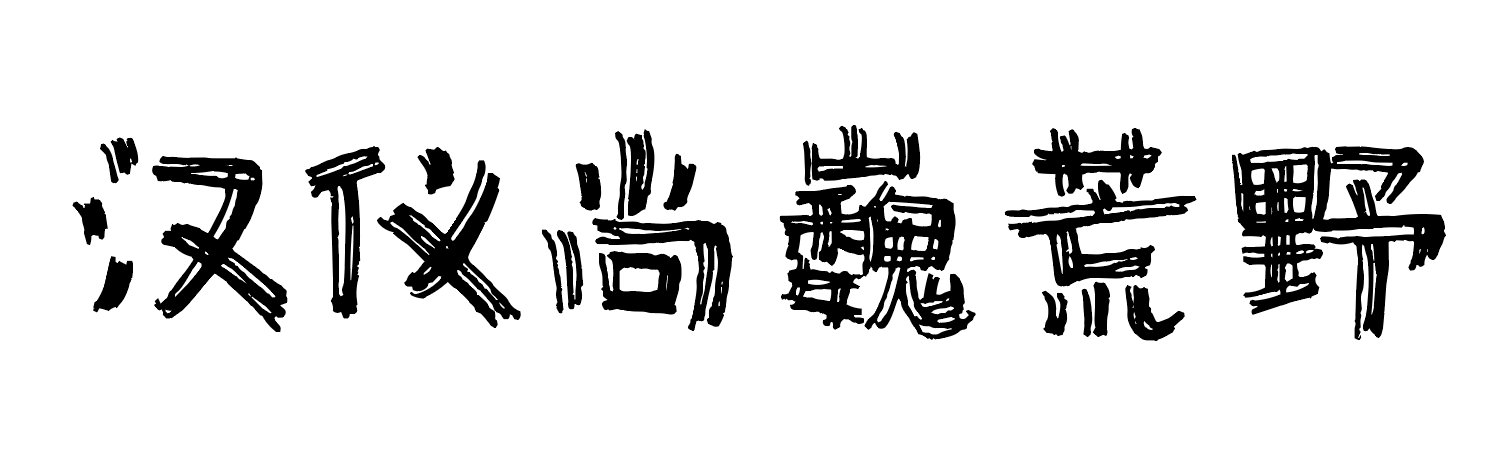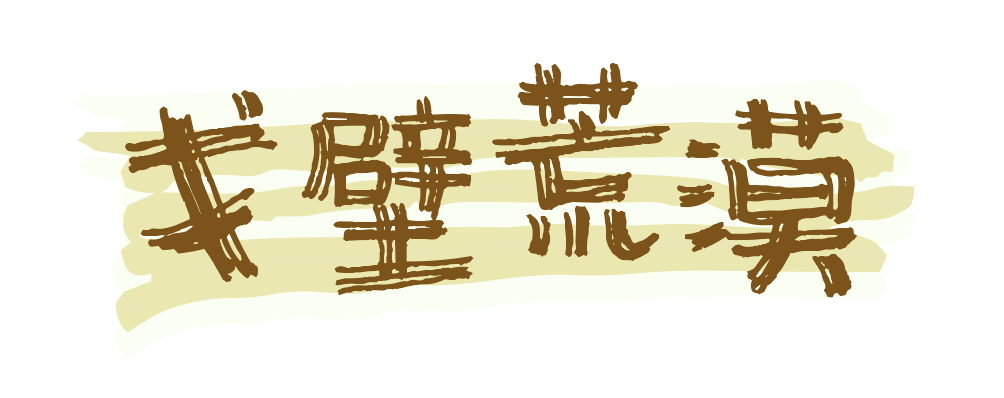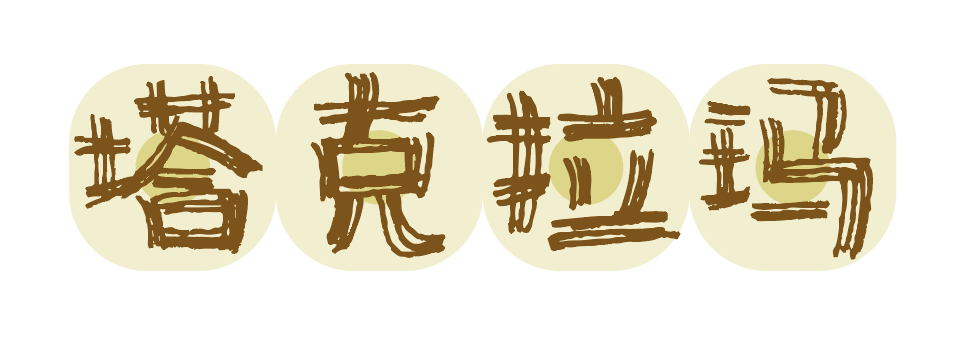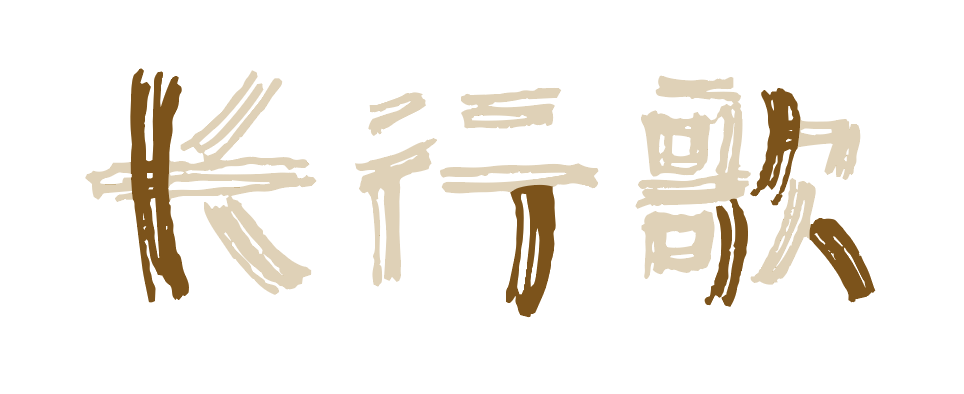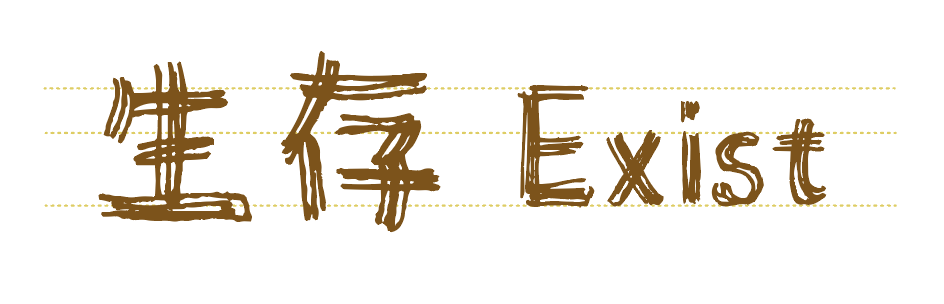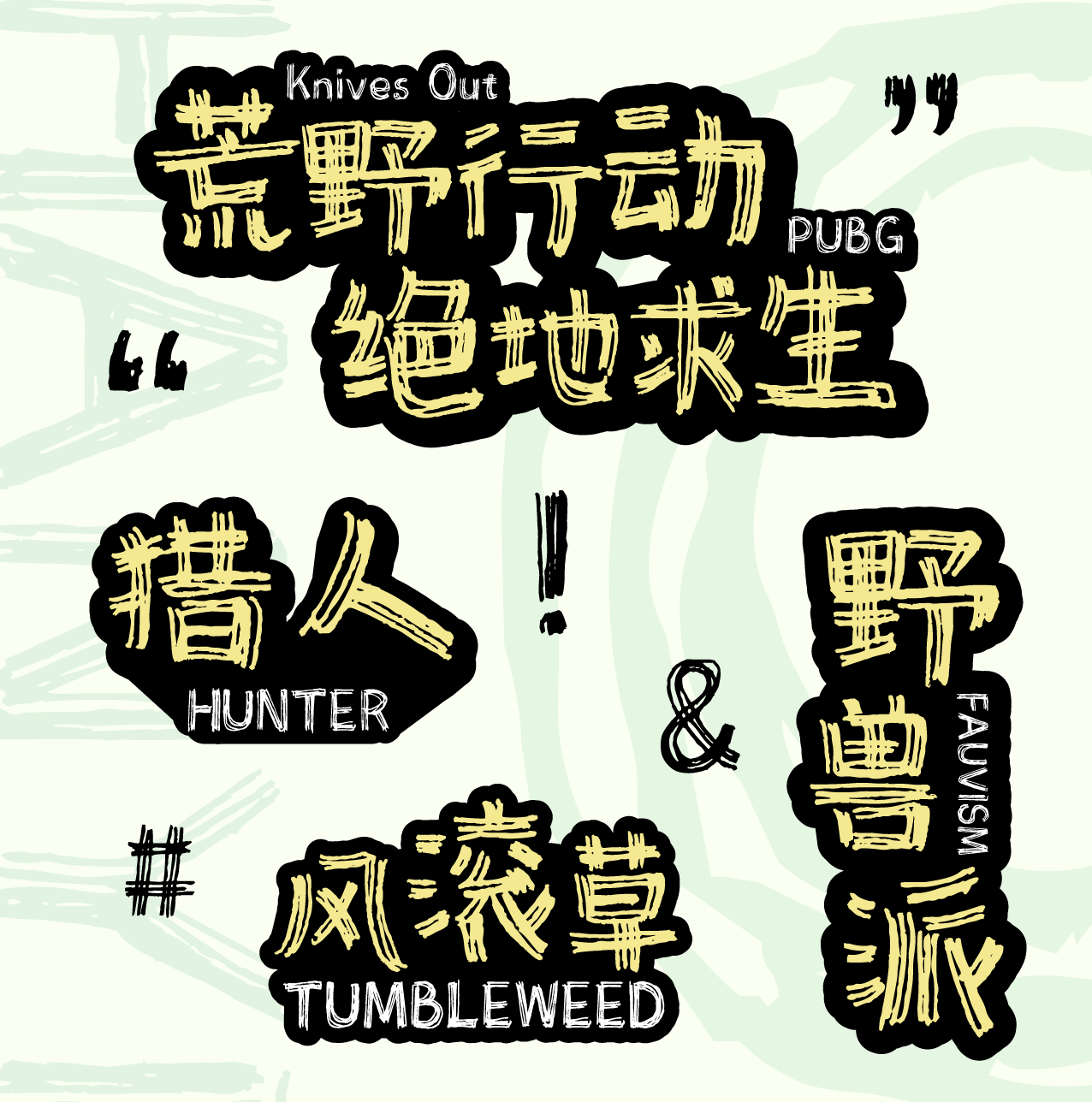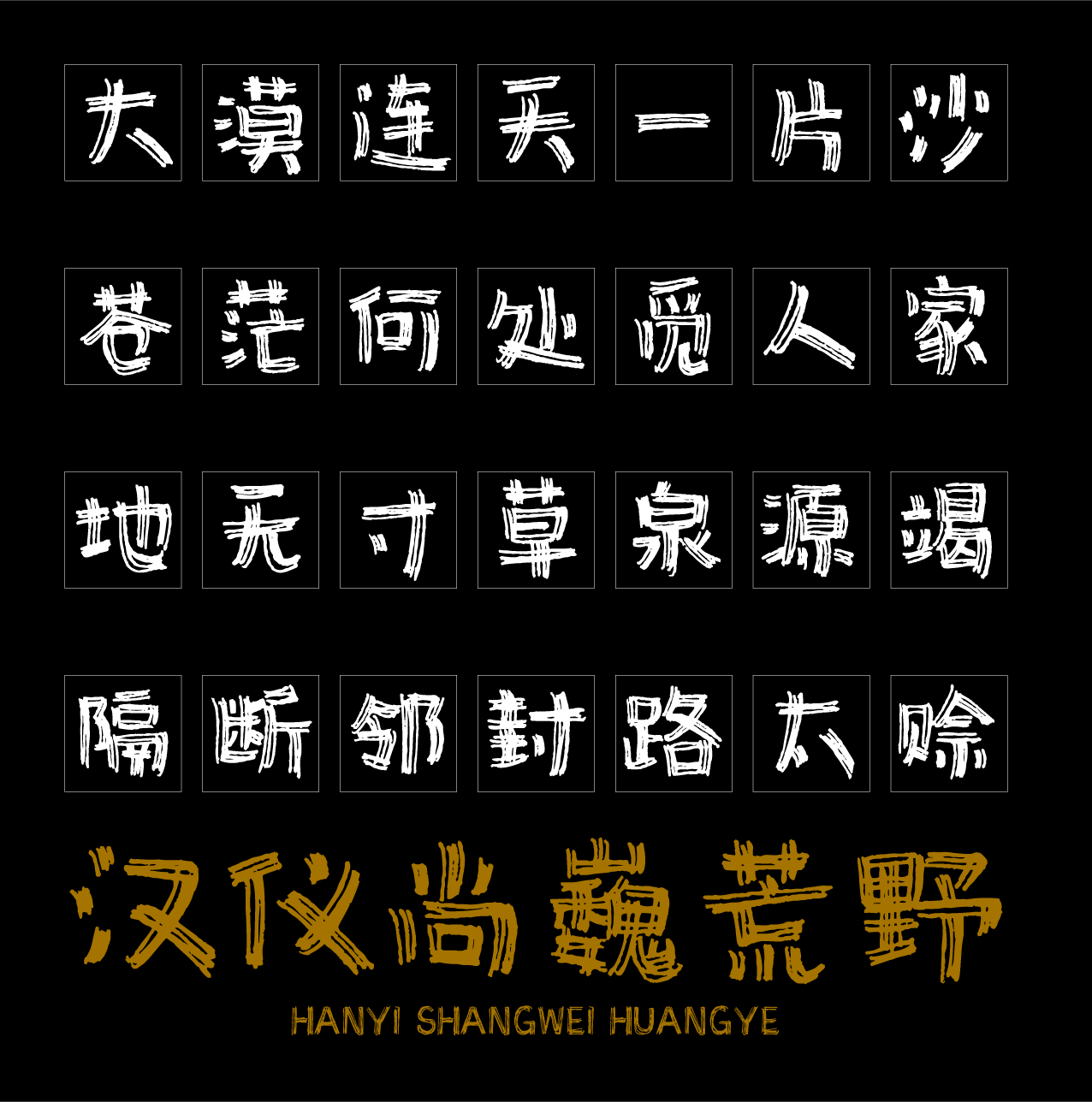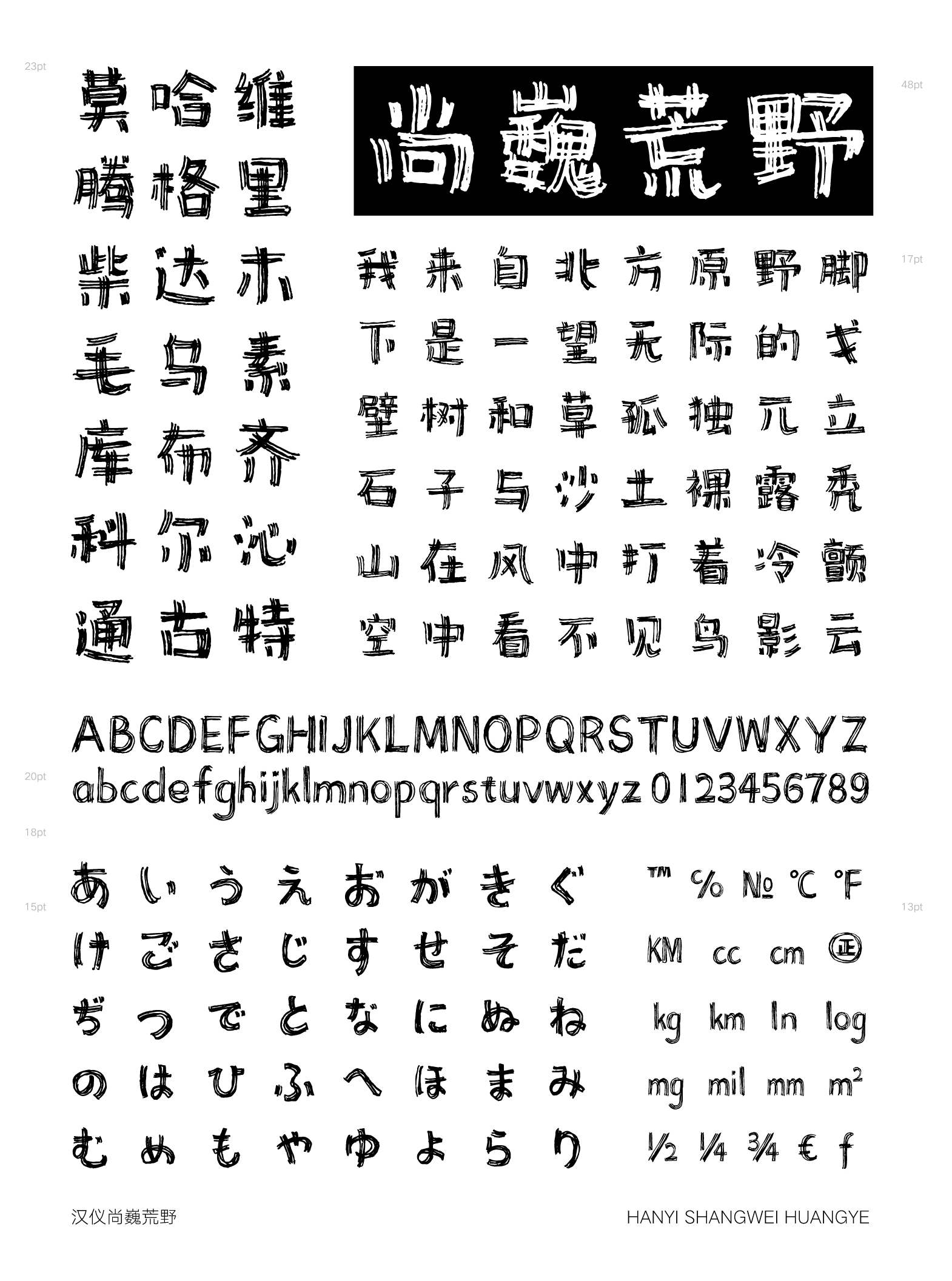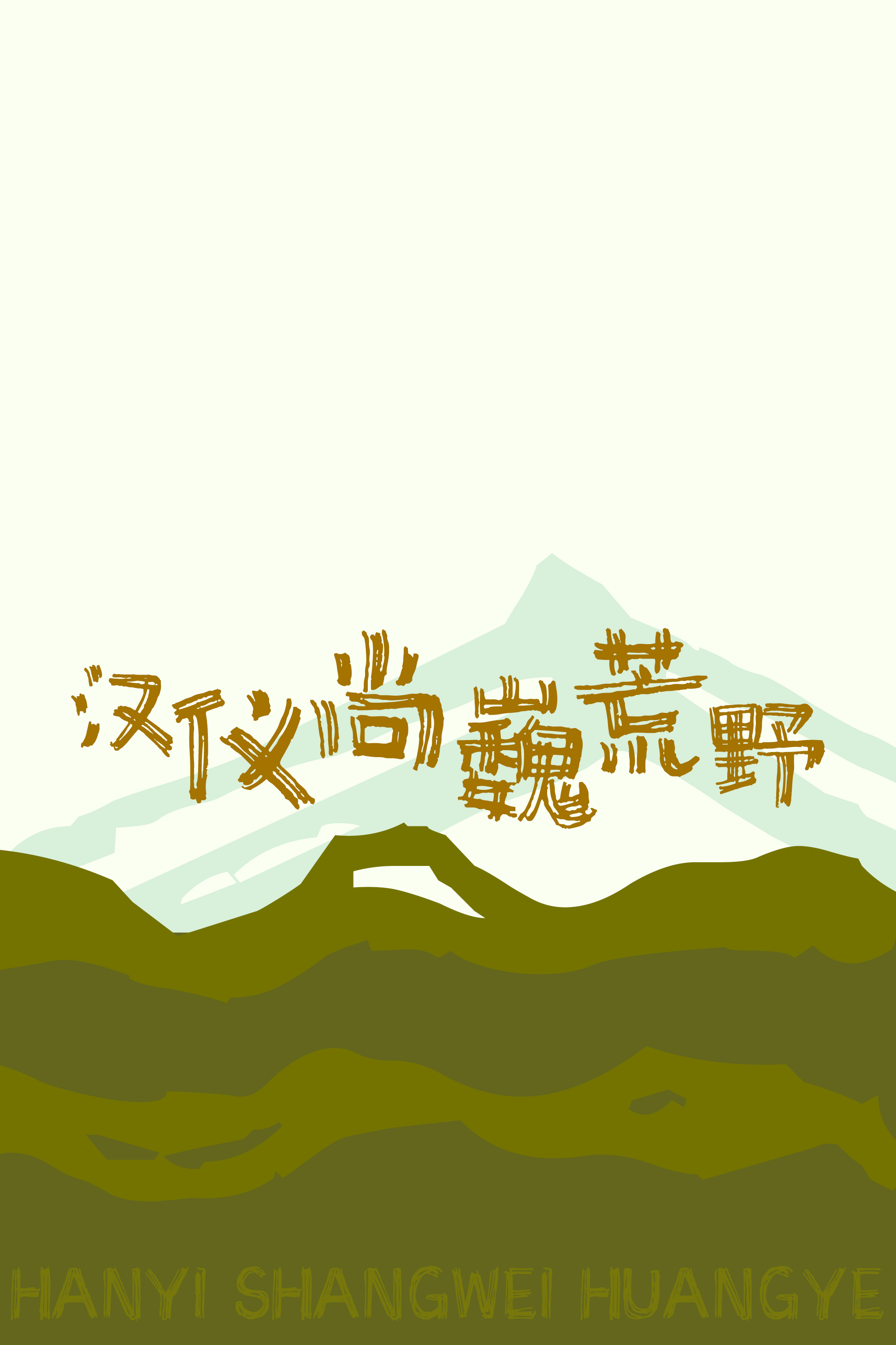
汉仪尚巍荒野字体介绍,汉仪尚巍荒野字体设计灵感
汉仪尚巍荒野|作者介绍
“汉仪尚巍荒野”出自汉仪字库签约设计师尚巍。他是一个行走于机打时代的手写人、跨界设计师、美学创意人、书法创作人;他是一位90后,却花了20年的时间不断诠释他对书法的情怀;他在这个浮躁的年代,坚持着自己的手写风格,不骄不躁;他被称作是一个带着传统,却敢倒立行走的新生代艺术家。
尚巍
笔染时光工作室主理人
独立设计师
知名设计自媒体
汉仪尚巍荒野|原生态
“汉仪尚巍荒野”是一款风格粗旷可爱的漫画手写体。字体自带纹理,就同它的名字一样,字形如旷野沟壑,笔画如枯枝,带给人新奇独特的视觉感受。
汉仪尚巍荒野|自带纹理
“汉仪尚巍荒野”运用排线的方式对字体本身进行重组,字与字之间的关系均衡舒适,诠释了一种新的手写体形式。
“汉仪尚巍荒野”的字形偏方,中宫宽绰,像是旷野上的草垛——蓬松、粗旷、原生态。使用时可以错落分布,也能整齐有序。
“汉仪尚巍荒野”的笔画保持着细腻的弧线曲度,弹性十足。使字体更加生动有趣、灵动活泼。
汉仪尚巍荒野|中西文匹配
“汉仪尚巍荒野”的西文同样运用了排线的书写手法,中西文搭配使用和谐统一。
汉仪尚巍荒野|排版样张
汉仪尚巍荒野|字体海报